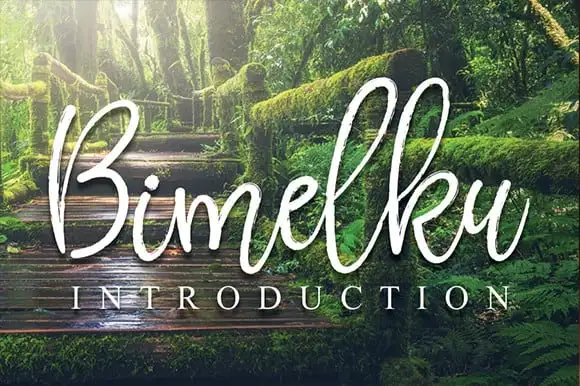
Bimelku Brush Font
A Bimelku Brush Font é uma elegante escolha para projetos que exigem um toque especial, seja na web ou no papel. Perfeita para ambientes digitais e físicos, esta fonte brush se destaca como uma opção excepcional para designs de wall displays, assinaturas de casamentos, logotipos de redes sociais, anúncios e embalagens de produtos. Suas linhas fluidas e arredondadas são idealmente adaptáveis a várias aplicações, desde as mais tradicionais como cartões de visita e materiais promocionais até os mais modernos como design para mídia social e criação de conteúdo digital. A Bimelku Brush Font é uma escolha versátil que não apenas adiciona um toque de estilo à sua marca ou projeto, mas também oferece a possibilidade de criar experiências memoráveis, seja em ambientes físicos ou virtuais.